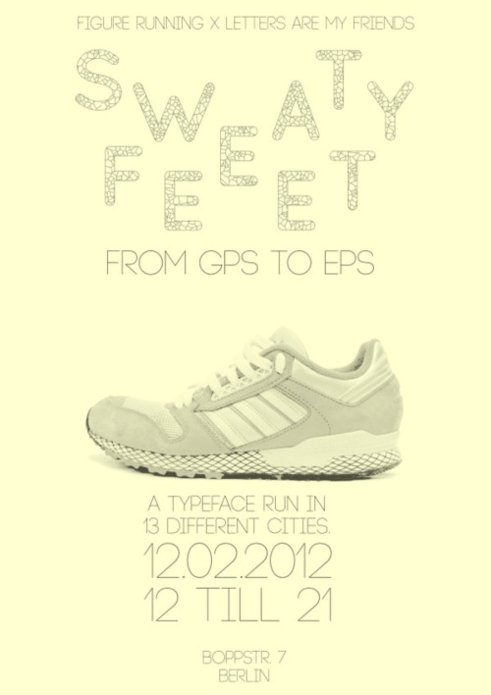
Im Oktober letzten Jahres haben wir euch auf Figure Running hingewiesen – Typo via GPS Gerät. Initiiert wurde das Projekt von Ingo Italic und nun ist es soweit: Die erste GPS generierte Schrift der Welt wird am Sonntag, den 12.02.2012 bei Letters Are My Friends veröffentlicht!
Aus dem Pressetext: People from all over contributet to our project initiated with Figure Running. This sunday we will be showing the results along with all the fun stories around each glyph - who ran it, where, why and how. No pedestrians where harmed in the making of this font!